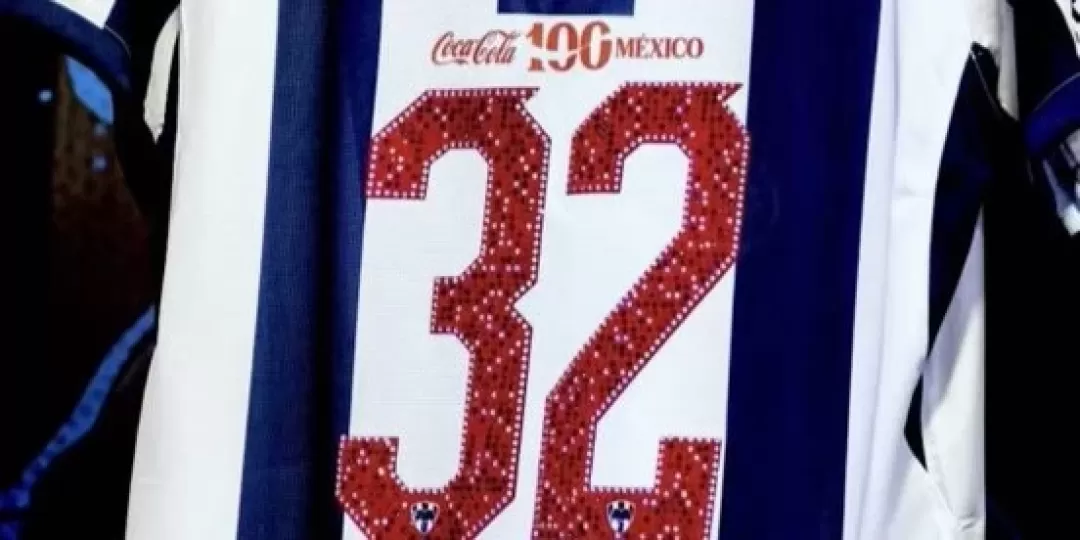
Monterrey utilizó una tipografía especial en los dorsales de su camiseta durante el partido frente a Cruz Azul, disputado en el Estadio BBVA. El diseño fue creado junto a Coca-Cola para conmemorar los 100 años de la compañía en México.
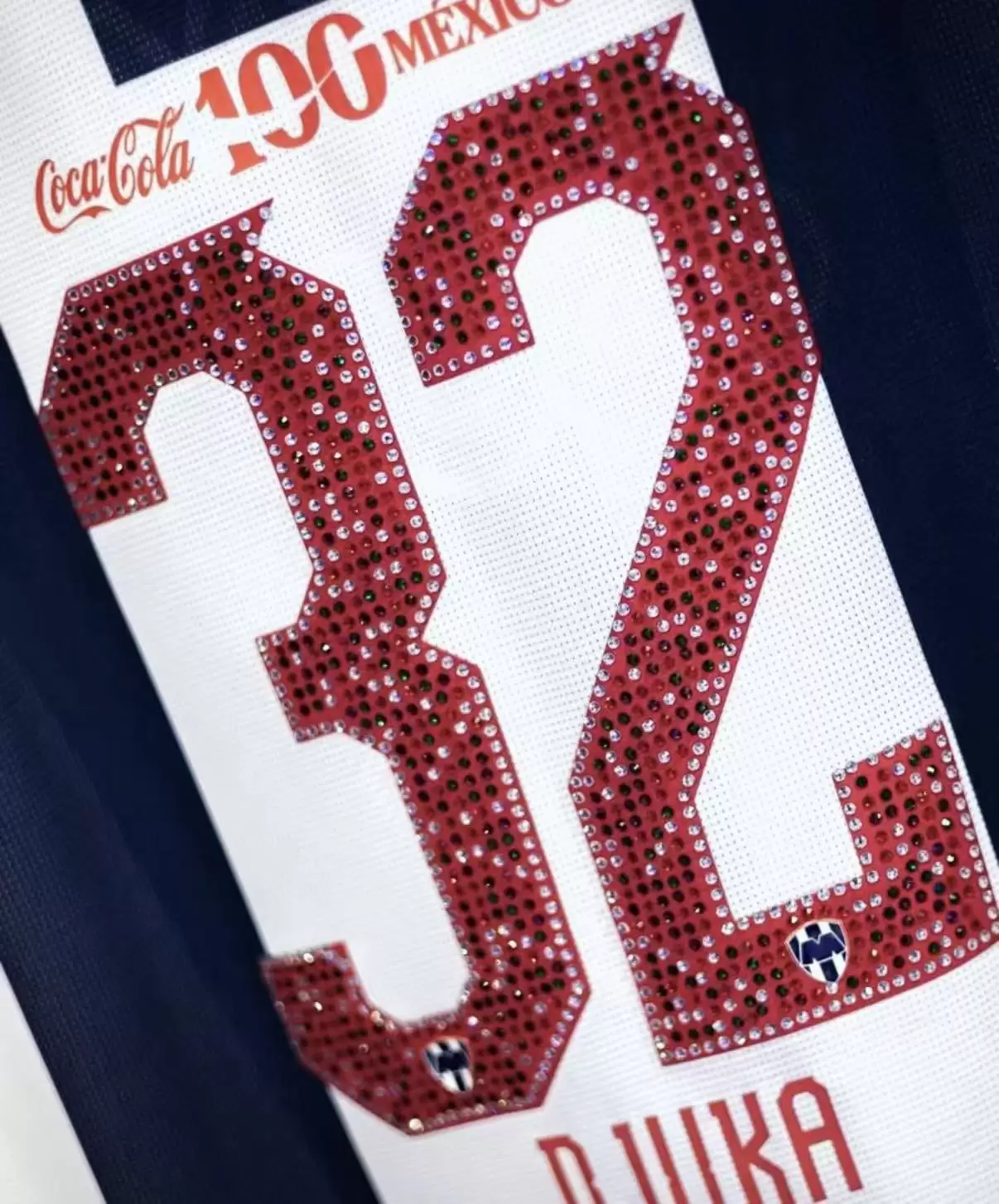
La tipografía presenta una base roja con detalles en blanco y verde, inspirados en elementos de la artesanía mexicana, además de incorporar un pequeño escudo de Rayados en los números. La edición también contó con una versión para coleccionistas, con solo 100 camisetas disponibles para personalizar en la tienda oficial del estadio.